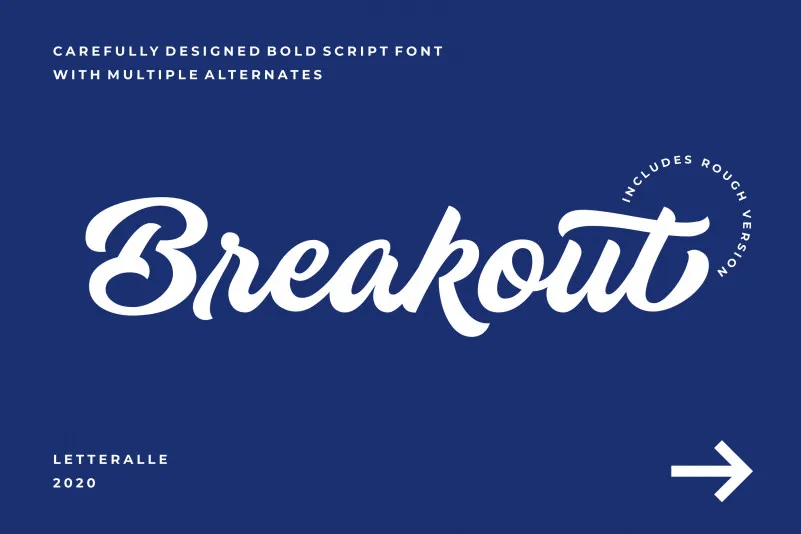
A Breakout Script Font é uma obra-prima para quem busca letras fluídas que transportam emoções por entre as palavras. Desenvolvida pelo Letteralle Studio, essa fonte traz um toque de frescura nas formas das letras, capturando instantes fugazes e sentimentos profundos em cada traço. Embora algumas letras possam parecer incompreensíveis, elas despertam emoções poderosas que podem transformar qualquer design. Em muitos casos na comunicação visual, as emoções passam a ser mais importantes do que os detalhes técnicos. Com a Breakout Script Font, o nosso cérebro pode descodear formas de letra como uma forma de linguagem universal e emocional. Esta é uma fonte de script perfeita para expressar sentimentos sutis em textos legais, adicionar um toque emotivo aos nomes da sua marca ou decorar letras finas em cartazes. A Breakout Script Font oferece a oportunidade de criar mensagens impactantes e memoráveis através de uma combinação única de formas artísticas e emoções expressivas. Não espere, descubra o poder do design emocional com essa fonte irresistível.